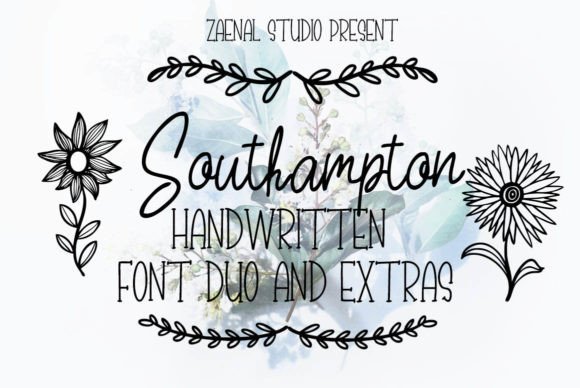
Southampton
หากคุณกำลังมองหาเนื้อหาคุณภาพสูงเช่น Southampton แพ็คเกจพรีเมียมนี้เป็นตัวเลือกที่ยอดเยี่ยมสำหรับโปรเจ็กต์สร้างสรรค์ของคุณ
ไม่ว่าคุณจะสร้างผลิตภัณฑ์ POD (Print on Demand) คำเชิญงานแต่งงาน หรือกราฟิกโซเชียลมีเดีย Southampton ก็เหมาะสมอย่างยิ่ง